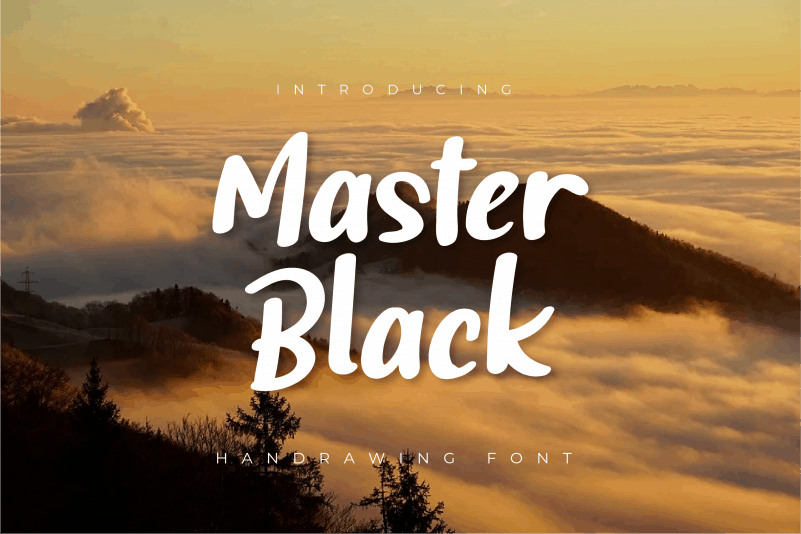
Master Black Script Font – Download Grátis
Master Black Script Font é uma exquisite fonte escrita a mão, meticulosamente projetada para se tornar uma verdadeira preferência. Se apaixone por sua versátil e inovadora estilo e use-a para criar designs espetaculares! Esta fonte escrita a mão apresenta um design único, que permite transformar qualquer texto em uma arte elegante e sofisticada. Suas curvas fluidas e detalhes cuidadosos fazem dela uma escolha única para estilos de design como editoriais gráficos, jornalismo digital ou até mesmo trabalhos publicitários. Master Black Script Font é ideal para quem deseja dar um toque único e personalizado aos seus projetos. Suas linhas leves e sua forma elegante permitem que você use esta fonte com confiança em qualquer tipo de projeto, desde o design de jornal até os arquivos de arte digital. Adquira a Master Black Script Font hoje mesmo e ofereça um toque distintivo aos seus projetos. Seu uso será uma escolha inteligente para quem busca estilizar suas criações de forma única e personalizada.